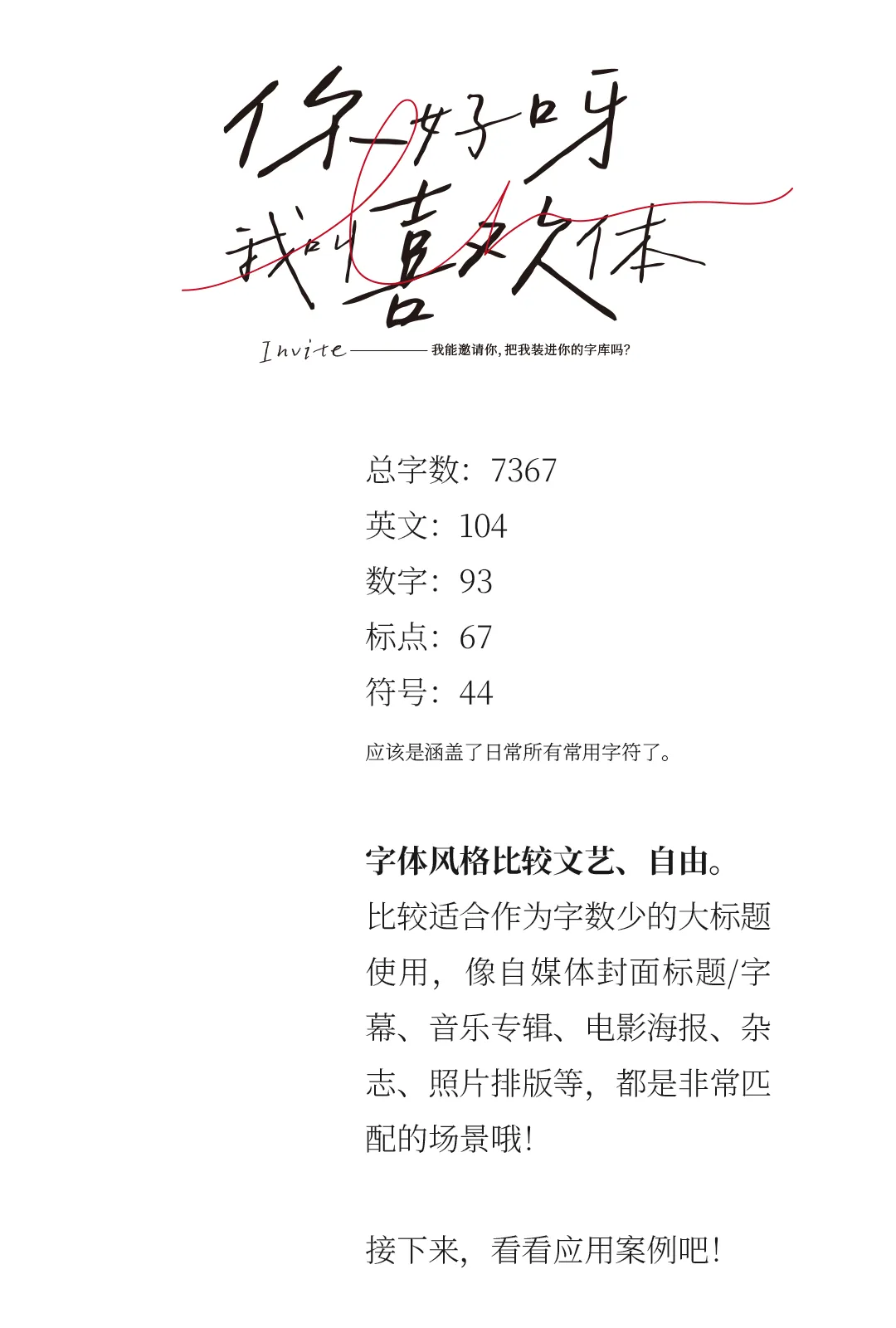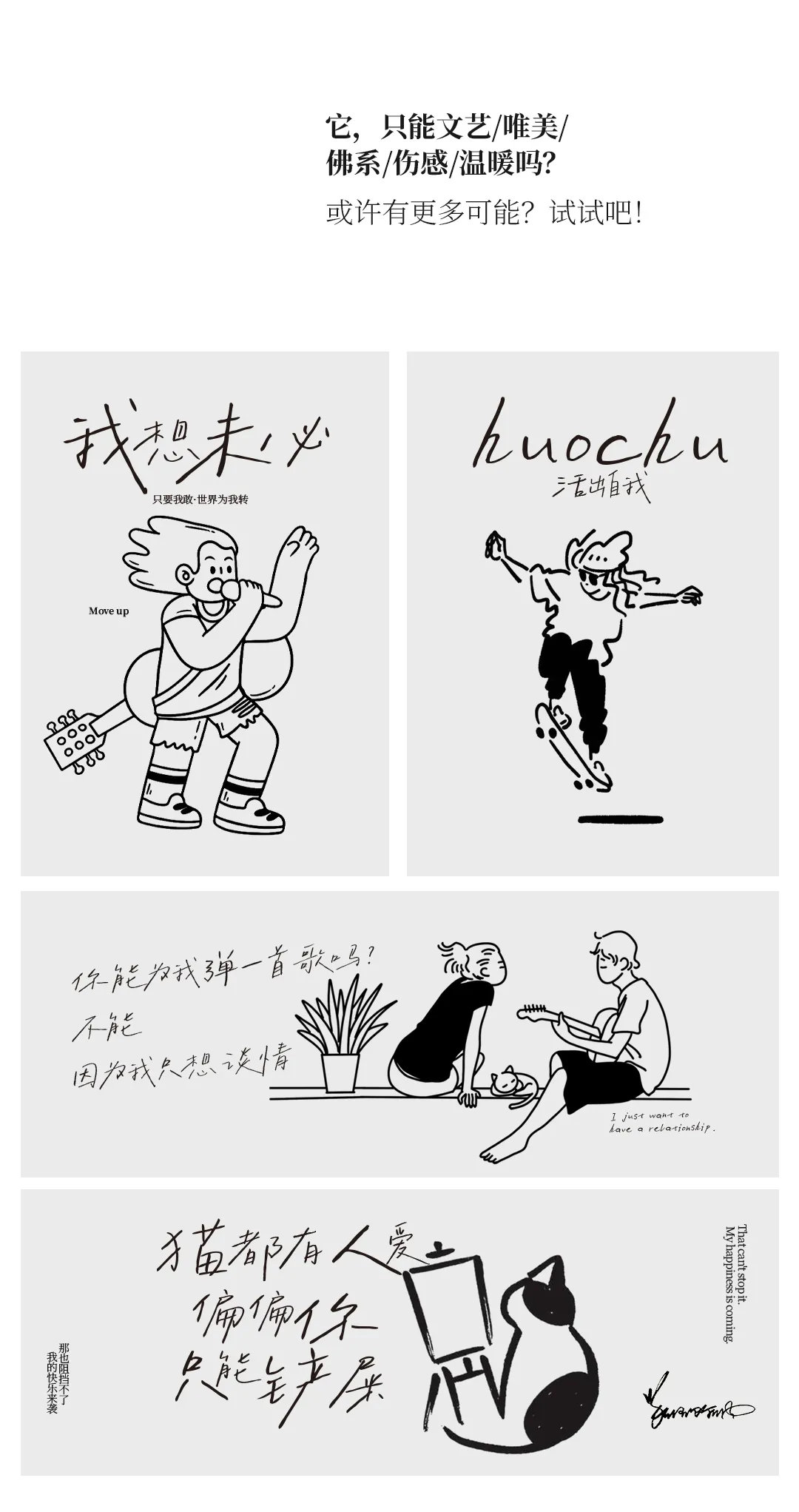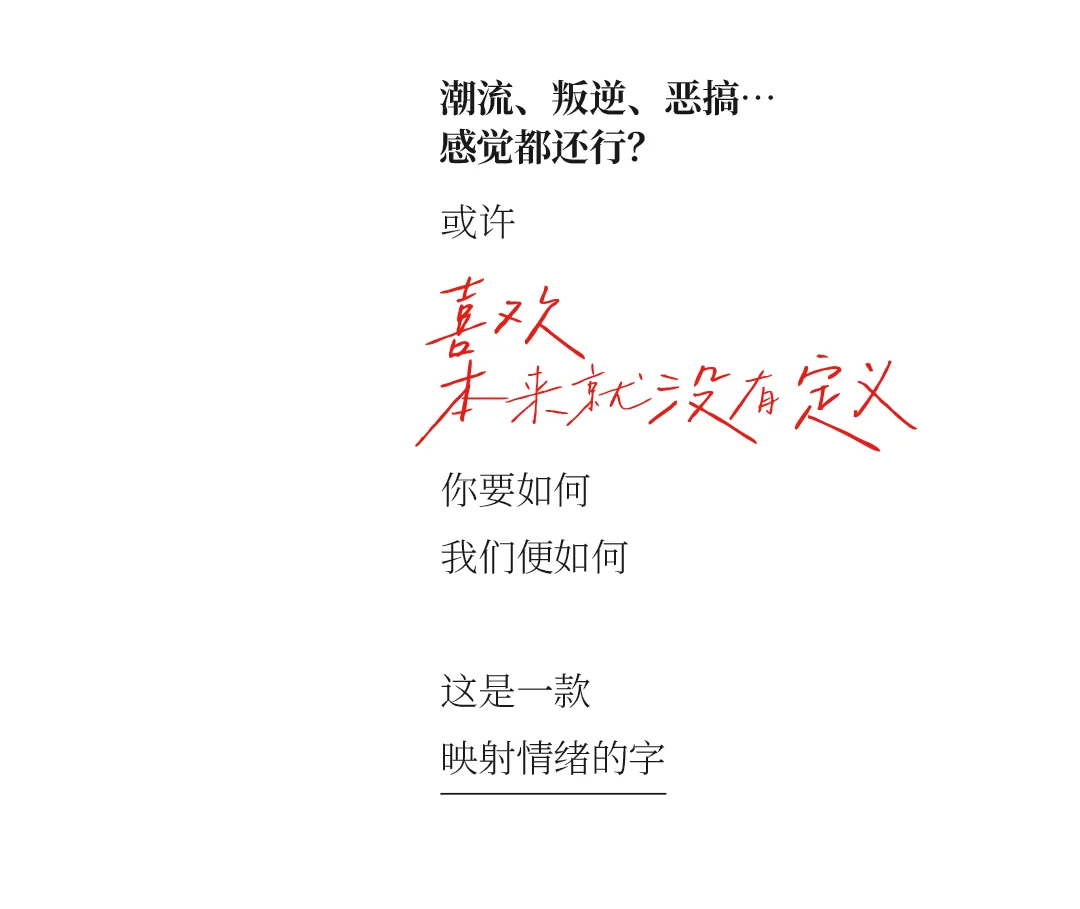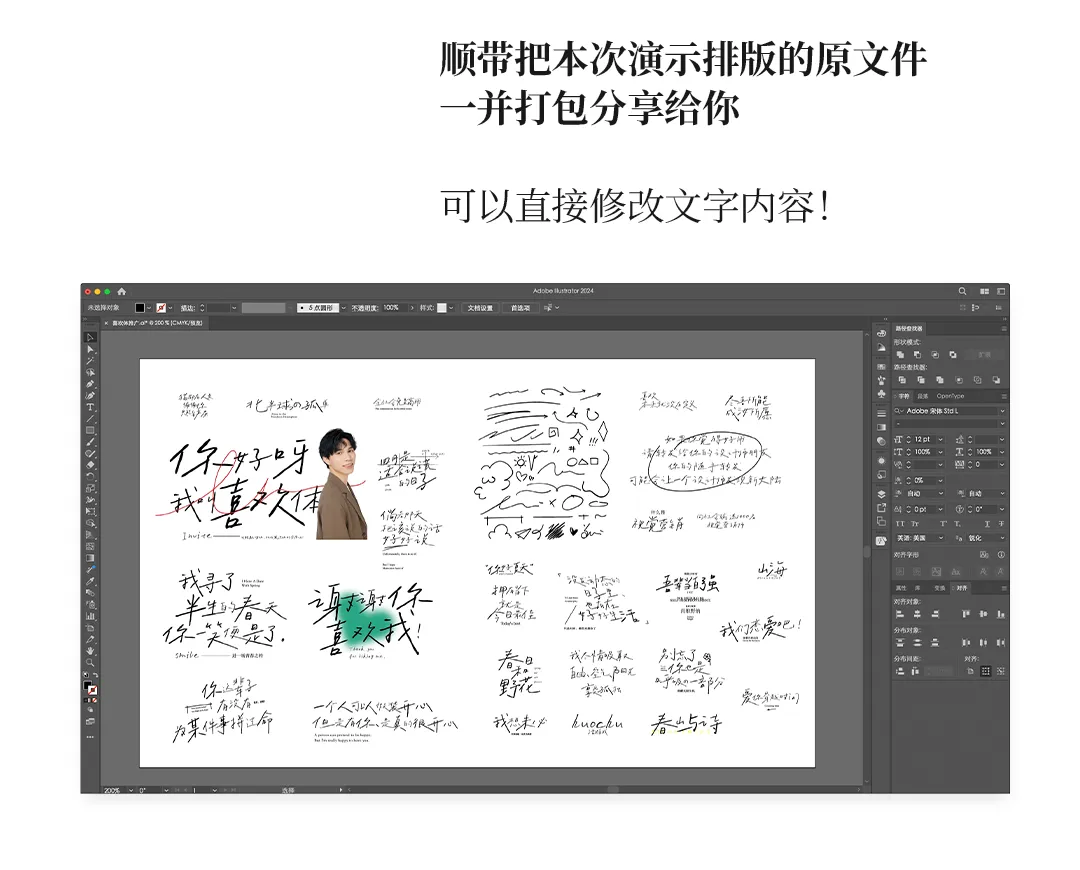
免费商用!喜脉喜欢体全新发布!
21年我们发布了第一款免费公益字体——喜脉体,至今已经过去3年了。
去年,在练习iPad手写的时候,想着要不索性写一套拙字吧,好看的写不出,但自然文艺有温度的还是可以试试的。于是我借鉴两款市面上已发布的手写体,进行了两者风格的结合,最终写了一套今天要送给大家的这份礼物。
它叫——喜脉喜欢体。
总字数:7367
英文:104
数字:93
标点:67
符号:44
应该是涵盖了日常所有常用字符了。
字体风格比较文艺、自由。比较适合作为字数少的大标题使用,像自媒体封面标题/字幕、音乐专辑、电影海报、杂志、照片排版等,都是非常匹配的场景哦!